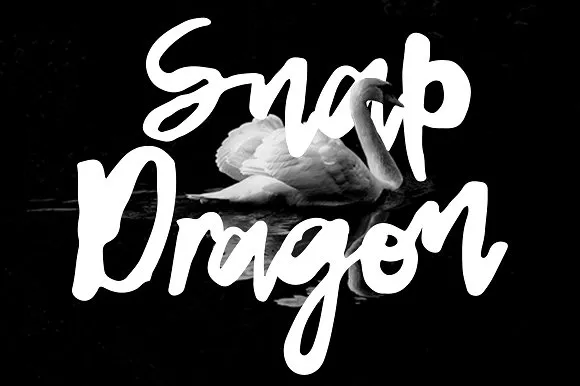
Snap Dragon Script Font – Download Grátis
Aqui está uma breve descrição para a página de download da font ‘Snap Dragon Script Font’, que segue as instruções fornecidas: ‘Introduzimos Snap Dragon Script Font, uma fonte premium criada por XXICREATIVE disponível na Creativemarket. Antes restrita à um pequeno número de acessos, agora está gratuita para download! Ideal para dar vida a seus designs e torná-los ainda mais únicos. Esta fonte é perfeita para adicionar aquela pitada especial em qualquer projeto. Use-a em cartões de notas ou nas palavras sobre belas fotos naturais, criando um toque que faz seu design realmente vibrar. Opa, o que você tem? Uma combinação completa: letras maiúsculas e minúsculas, números e pontuação para dar vida a tudo do qual deseja usar esta fonte. Seu trabalho gráfico vai brilhar com Snap Dragon Script Font.’